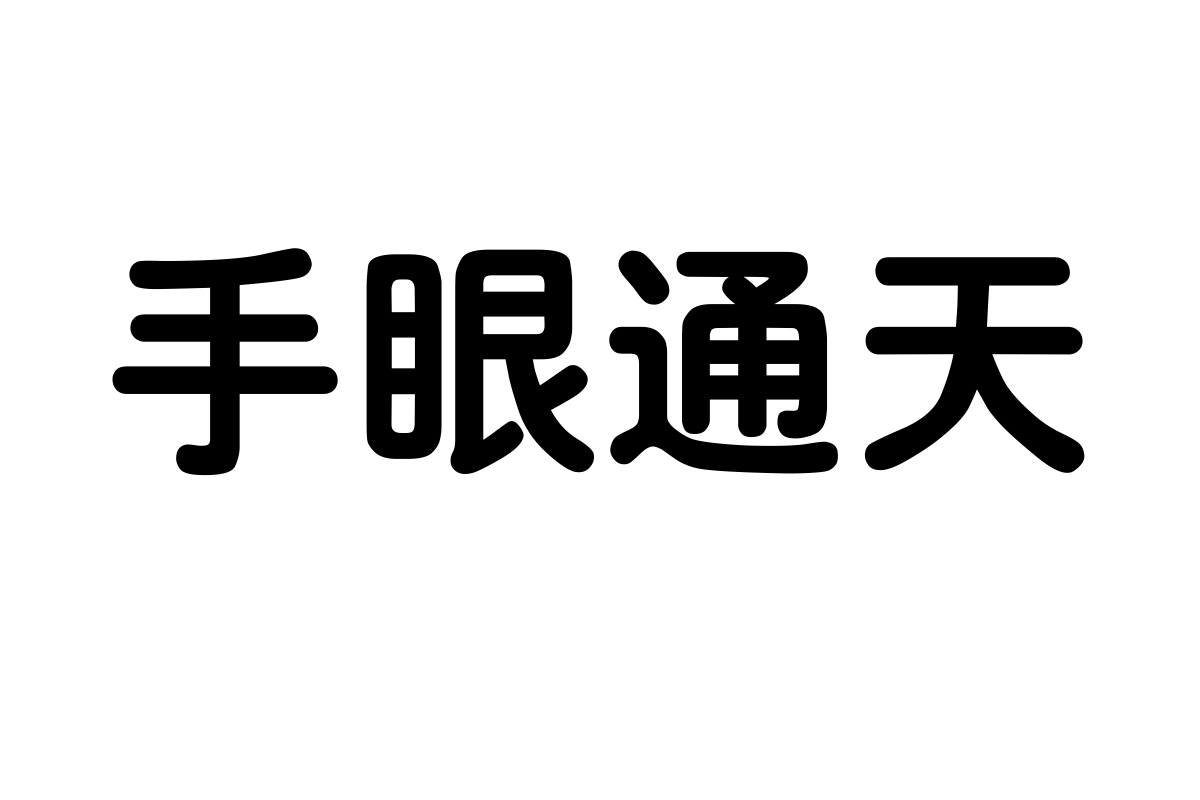
汉仪粗圆简是一款非常实用的中文字体,它的特点是字形粗壮、笔画清晰。这款字体适合用于标题、广告、报纸等需要强调视觉效果的场合。同时,它也适用于各种印刷品和电子媒体,如网站、手机屏幕等。
汉仪粗圆简采用了简洁的设计,使得字体看起来更加醒目和易于阅读。它的笔画粗细适中,既不会过于繁琐,也不会显得单调。这使得它在视觉上给人一种强烈的冲击力,能够迅速吸引人们的注意力。
此外,汉仪粗圆简还具有较好的适应性。无论是在哪种设备上使用,它都能够保持其独特的风格和效果。无论是在传统的印刷品上,还是在现代的数字媒体上,它都能够展现出其独特的魅力。
总的来说,汉仪粗圆简是一款非常适合商业和设计用途的字体。它不仅能够帮助您创造出引人注目的视觉效果,还能够提升您的设计作品的整体品质。